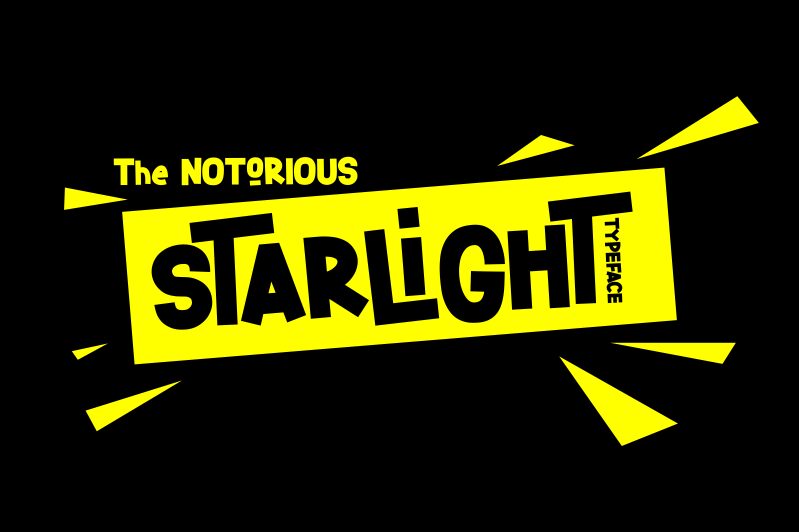
Starlight, eine verspielt-fette Display-Schrift von nami_studio, bringt eine spielerische Note ins Spiel, die man einfach nicht ignorieren kann. Mit ihrem Cartoon-Stil, der Charme und Spaß versprüht, fängt diese Schriftart die Essenz unbeschwerter Kreativität ein und verleiht jedem Buchstaben eine eigene Persönlichkeit. Die kräftige Strichstärke sorgt für eine solide Präsenz in jedem Design und lässt Ihre Botschaft selbstbewusst und fröhlich hervorstechen.
Die abgerundeten Kanten und freundlichen Kurven von Starlight machen sie zur idealen Wahl für Projekte, die eine Balance zwischen nahbarer Wärme und ausdrucksstarker Wirkung suchen. Ob Sie ein Kinderbuchcover gestalten, einen animierten Vorspann entwerfen oder eine Casual-Gaming-App branden – Starlight bietet Vielseitigkeit in einem ästhetisch ansprechenden Paket.
Verleihen Sie Ihrem nächsten kreativen Projekt den unbeschwerten Geist von Starlight, bei dem Persönlichkeit im Vordergrund steht, und lassen Sie Ihre Designs mit einer ansteckenden Energie strahlen, die den Betrachter einfach zum Lächeln bringt.